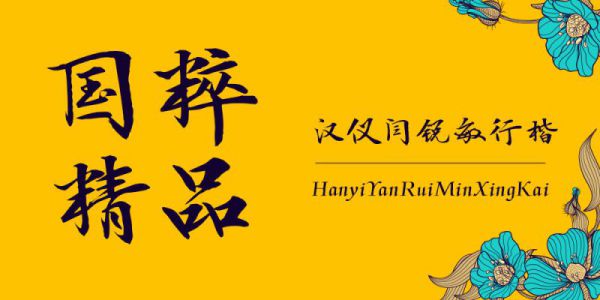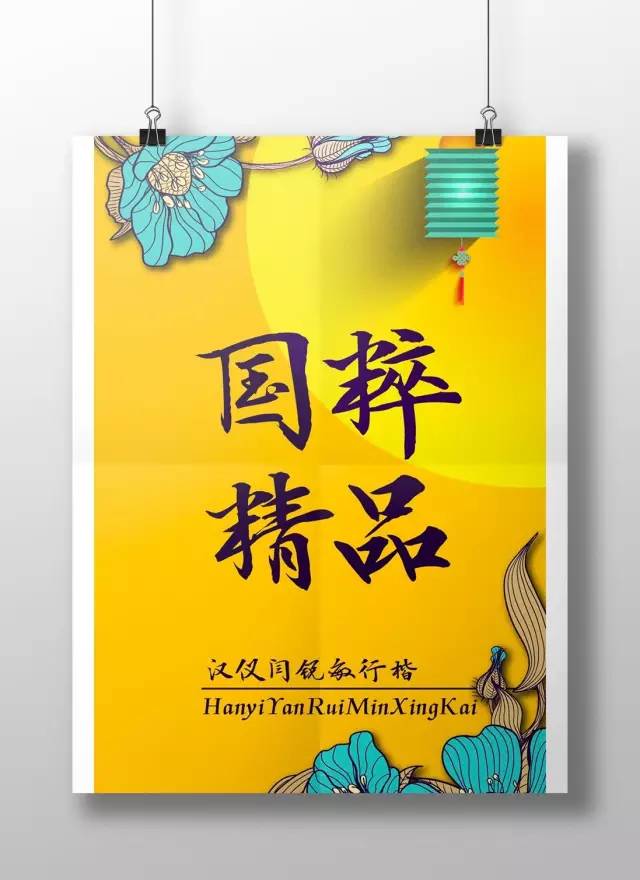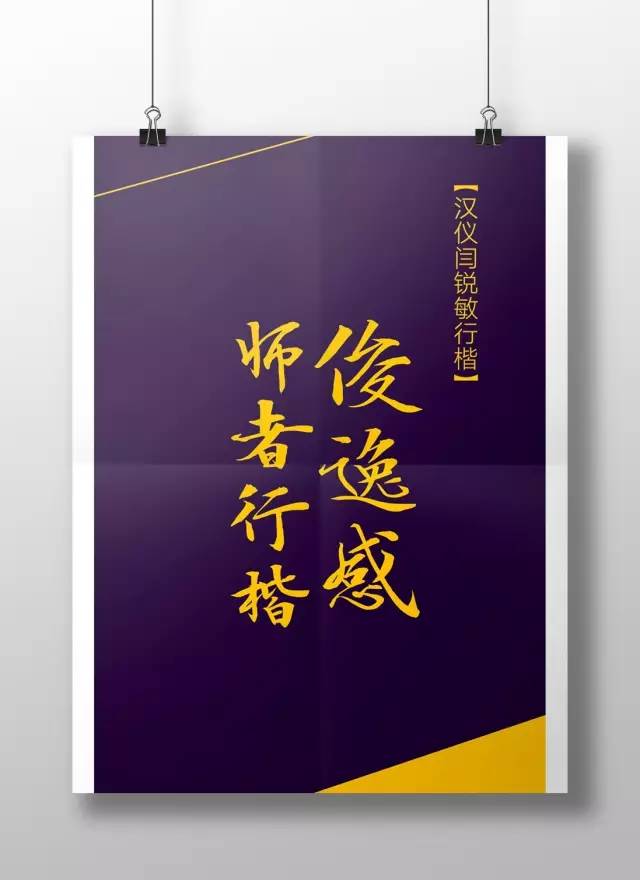
汉仪闫锐敏行楷 | 俊逸感师者行楷
阎锐敏
应用范围推荐
大标题/ 古籍排版/ 包装
字体气质 韵动/ 典雅 / 俊逸/ 中国风
应用环境 书籍/游戏/ 中国文化/教育/ 旅游/ 餐饮等
产品规格
汉仪闫锐敏行楷 | HYYanRuiMinXingKai
9169字 | 中文简繁+网络字
阎锐敏老师虽然也是以楷书名世,但他对魏碑、二王、晋人写经、宋元明清及至现当代艺术,一路都曾下过苦功。他的眼界很宽,无论传统的,还是现代的,凡是优秀的、经典的、自己喜欢的,都会去学习借鉴,吸收消化。他的思想里有非常强的包容性,这不仅表现在书法上,生活中的其他方面也是如此,他爱生活,爱美食,爱高科技,更爱艺术,对新鲜事物的好奇心滋润和影响着他的个人性情、人格气质、笔墨情趣和价值观念,继而丰富了他的艺术创作灵感。
褚遂良《雁塔圣教序》及《阴符经》中“用笔空灵”、“离纸一寸”笔法,阎锐敏曾经悉心参悟,故而用笔结体则敢于在严谨规范中越雷池而开创自我面貌。他的楷书从其线条、结字、体势上看,取魏碑之古朴,弃其凝重;取隶书之舒展,弃其刻板;取行书之灵动,弃其轻飘;取颜体之宽博,弃其雄厚;取欧体之险峻、清雅,弃其瘦硬、紧凑;取虞世南之温润,弃其阴柔;取赵孟頫之潇洒,弃其滑媚……笔随心动,美不胜收。他“以行书写楷书”的笔法尝试,极大地提高丰富了楷书线条的表现力和其楷书独有的信息含量,给人带来一种视觉审美的外延和精神的愉悦。综观其楷书高秉古脉,仪态大方,端庄疏朗,丰秀相宜,劲而不僵,古而不滑,传统而不死板,现代而不飘浮,韵味十足,俊美无比。以其楷书的功力,再用行楷书写《兰亭集序》,结果是疏密相间,动静分明,潇洒婉畅,典雅自然,神采飞扬,气脉非凡,堪称妙品。
阎锐敏老师的楷书经过几十年的探索发展,基本形成了自己个性突出的“阎体”。让人在众多楷字中一眼便能分辨,这是他孜孜创新以求得的成功,他以最大的勇气在古人楷书法则中探寻出了一条属于自己的表述范式,树立了自己的一面旗帜,闯出一片天地。
1975年,阎锐敏开始师从刘宗继先生。1996年毕业于首都师范大学书法专业,现为北京市书法家协会会员、炎黄书画家协会主席、中国人民大学硕士研究生书法导师、解放军艺术学院客座教授,此外他还担任着许多社会职务。
阎锐敏老师擅长书法教学,立志为普及书法做贡献。他在北京的少年宫、文化馆、少年之家、大、中、小学、党政机关等十多个单位讲授书法,深受欢迎。据不完全统计,经他教过的学生已达数十万之众,仅面授学生就有十几万人,在全国获奖率高达30%,有的学生已经进入各种书法组织的领导岗位,有的学生则走上书法讲台。
斗方《传家有道》
斗方《好书不厌看》
斗方《泡茶要诀》
斗方《墙角数枝梅》
斗方《唯其不是而常是》
斗方
斗方李白诗
隶书中堂 杜小山诗《寒夜》
隶书中堂 苏轼诗《海棠》
行楷对联 传家有道惟忠厚 处世无奇但率真
行书园光 白居易诗《钱塘湖春行》
篆书 自强不息